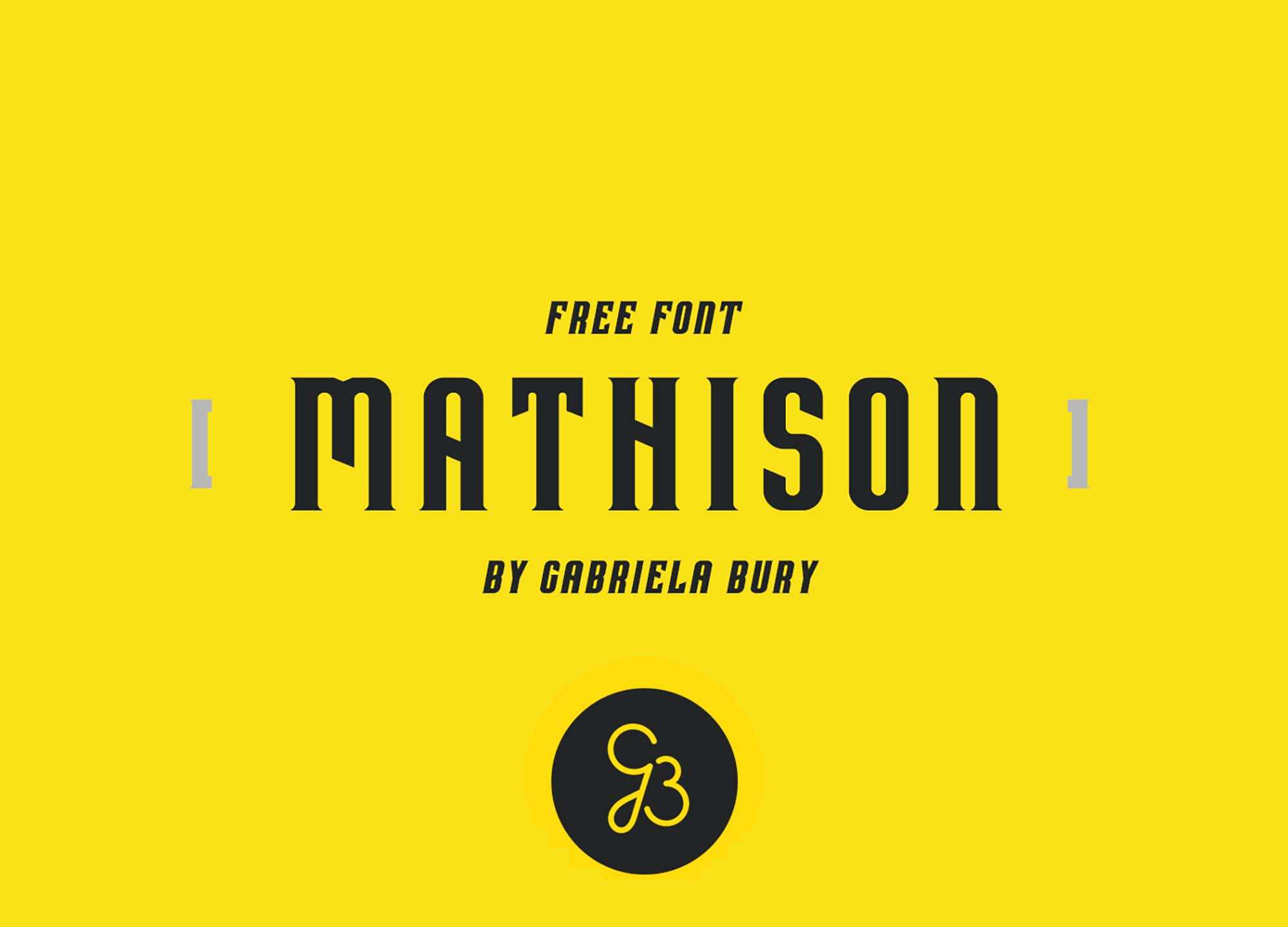
Mathison Display Font – Download Grátis
Este novo tipo de fonte chamado Mathison foi criado pela designer Gabriela Bury. Ele se soma à coleção de fontes modernas, apresentando linhas retas e formas sólidas em uma coleção de letras maiúsculas e números, um conjunto que transmite confiança em cada caractere. Mathison vem com várias pesos, incluindo regular, bold, italic e bold italic, permitindo que você personalize o estilo e use-o para ambientes pessoais e comerciais. O design da Mathison é tão versátil quanto a simplicidade de uma fonte sans serif, oferecendo aos criadores e designers a oportunidade de criar ambientes de escrita modernos e estilizados.